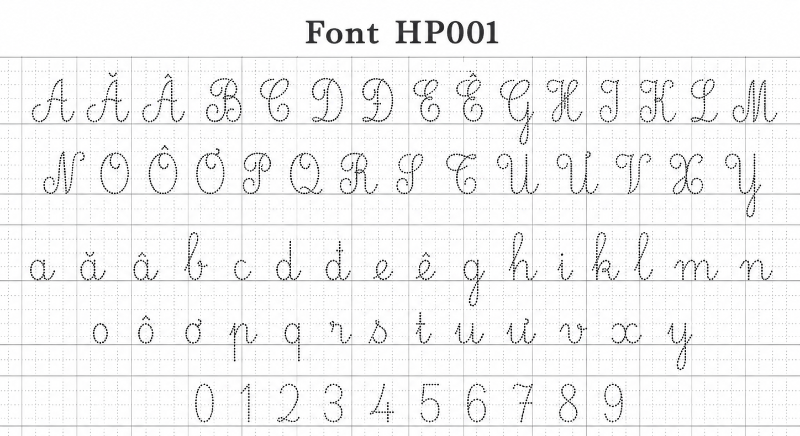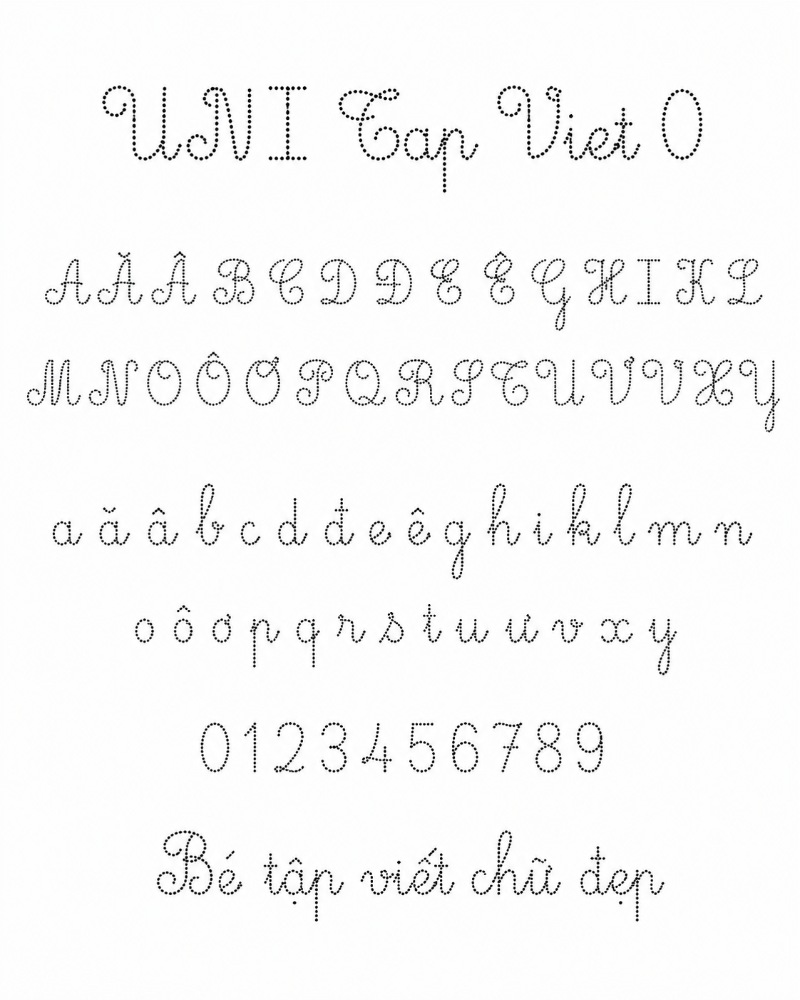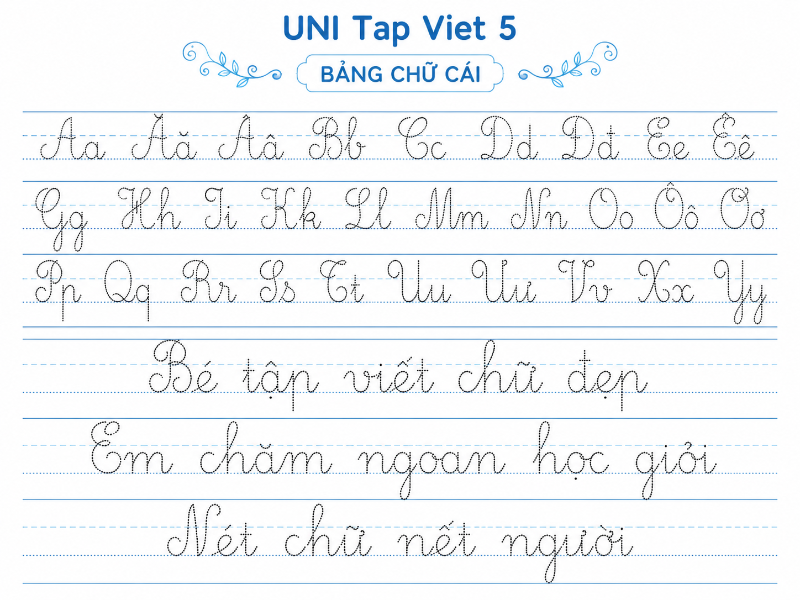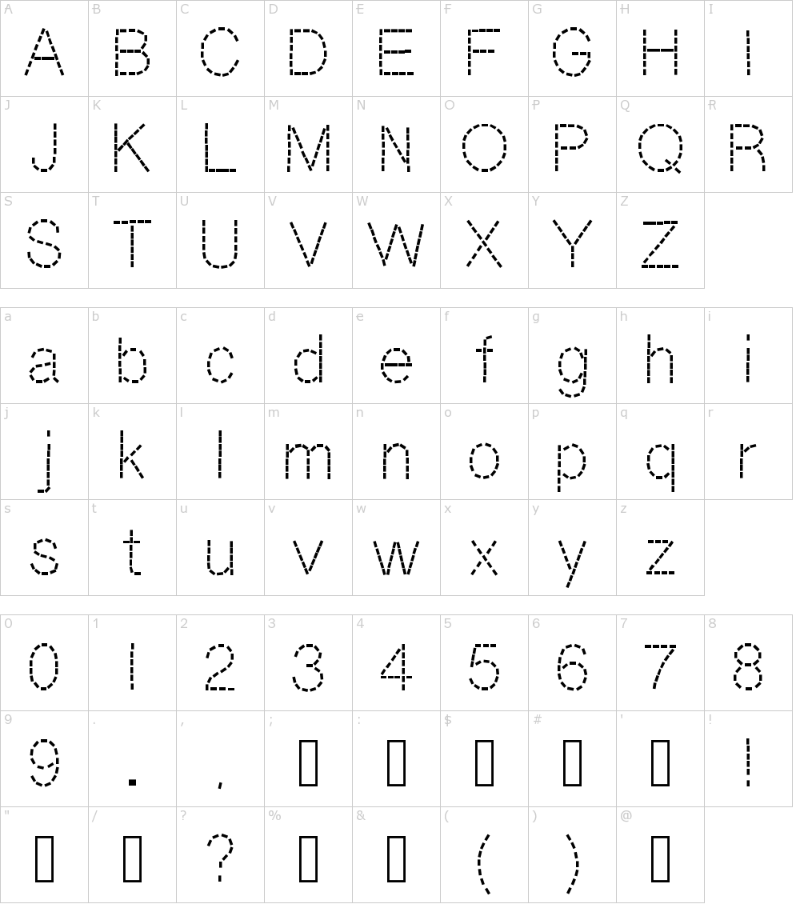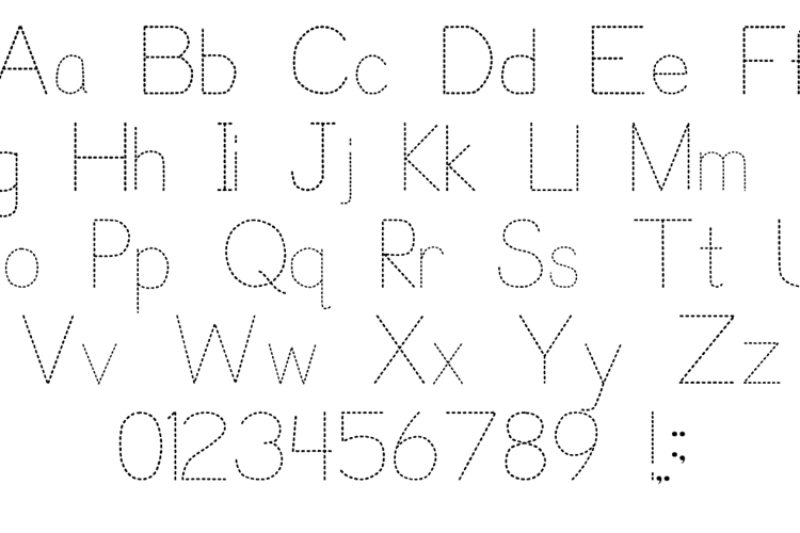
Chia sẻ 5+ Font chữ nét đứt việt hóa đẹp, dễ ứng dụng
Bạn đang mất thời gian tìm kiếm một font chữ nét đứt để thiết kế phiếu tập viết, worksheet cho bé luyện chữ tại nhà? Hoặc bạn là designer đang cần một kiểu chữ độc đáo, mang cảm giác hiện đại, công nghệ để tạo điểm nhấn cho logo, bao bì hay ấn phẩm truyền thông? Dù sử dụng với mục đích nào, bạn chắc chắn sẽ gặp một vấn đề quen thuộc: font nét đứt có rất nhiều, nhưng font hỗ trợ tiếng Việt tốt, không lỗi dấu và khi in ra vẫn rõ nét thì lại không dễ tìm.
Thực tế, không ít người tải font về, cài đặt xong và bắt đầu sử dụng, nhưng khi gõ tiếng Việt có dấu thì chữ bị lệch, lỗi ký tự hoặc tự động chuyển sang font mặc định khiến thiết kế trở nên rối mắt và thiếu chuyên nghiệp. Vì vậy, trong bài viết này, In Đại Minh sẽ tổng hợp và chia sẻ đến bạn những font chữ nét đứt đẹp, dễ dùng, phù hợp cho cả học tập, in ấn và thiết kế sáng tạo.
Font chữ nét đứt là gì?
Font chữ nét đứt, hay còn gọi là Dotted Font hoặc Dashed Font, là kiểu chữ được tạo nên từ các đường nét ngắt quãng. Thay vì liền mạch như font thông thường, từng ký tự sẽ được cấu thành bởi các chấm nhỏ hoặc những đoạn gạch rời nối tiếp nhau, tạo cảm giác rõ nét, dễ nhận diện và rất phù hợp cho nhiều mục đích sử dụng khác nhau.
Font chữ nét đứt
Hiện nay, font chữ nét đứt không chỉ xuất hiện trong các tài liệu học tập mà còn được ứng dụng rộng rãi trong thiết kế sáng tạo.
Trong lĩnh vực giáo dục, đây là một trong những công cụ quen thuộc với giáo viên tiểu học, giáo viên mầm non và phụ huynh. Font nét đứt thường được dùng để thiết kế phiếu bài tập, mẫu chữ tập tô, vở luyện viết chữ cái hoặc tài liệu rèn nét cho học sinh lớp 1. Nhờ các nét chữ được chia thành từng đoạn nhỏ, trẻ có thể dễ dàng quan sát, tô theo và làm quen dần với cách điều khiển nét bút.
Trong thiết kế đồ họa, font nét đứt lại mang đến một phong cách hoàn toàn khác. Các designer thường chọn những kiểu font nét đứt có dáng chữ mạnh, cứng cáp hoặc góc cạnh để tạo logo, poster thể thao, banner công nghệ, ấn phẩm sci-fi hoặc các thiết kế typography nổi bật. Kiểu chữ này giúp nội dung trở nên cá tính hơn, tạo điểm nhấn thị giác và tăng tính sáng tạo cho sản phẩm thiết kế.
Top các bộ font chữ nét đứt Việt hóa chuẩn hiện nay
Hiện nay có khá nhiều bộ font chữ nét đứt được chia sẻ trên mạng, nhưng không phải font nào cũng hỗ trợ tiếng Việt tốt. Dưới đây là một số bộ font đã được Việt hóa cẩn thận, hạn chế tối đa tình trạng lỗi dấu, lệch chữ hoặc tự động nhảy sang font mặc định khi sử dụng.
UNI Tap Viet 5
UNI Tap Viet 5 là bộ font rất phù hợp cho giáo dục, đặc biệt là làm vở tập viết lớp 1. Font có sẵn 5 dòng kẻ ô ly chuẩn tiểu học, nét đứt rõ ràng, giúp trẻ dễ nhìn và dễ tô theo. Bộ font này hỗ trợ cả bảng mã Unicode và VNI nên khá tiện khi dùng trên nhiều phần mềm khác nhau.
Font chữ UNI Tap Viet 5
UNI Tap Viet 0
UNI Tap Viet 0 có thiết kế đơn giản hơn vì chỉ gồm phần chữ nét đứt, không kèm đường kẻ nền phía sau. Đây là lựa chọn phù hợp để làm flashcard, bảng chữ cái, tài liệu nhận diện chữ hoặc các mẫu luyện viết cần bố cục thoáng. Font cũng hỗ trợ Unicode và VNI, giúp người dùng dễ nhập tiếng Việt có dấu.
Font chữ UNI Tap Viet 0
Trace Font
Trace Font gây thiện cảm nhờ kiểu nét đứt bo tròn, mềm mại và dễ nhìn. Font này đặc biệt phù hợp với worksheet mầm non, tài liệu tập tô chữ cái hoặc các bài luyện chữ cho trẻ nhỏ. Khả năng hiển thị tiếng Việt của Trace Font khá tốt, nhất là khi dùng với bảng mã Unicode.
Trace Font
Dashness
Dashness là kiểu font nét đứt có phong cách tối giản, thanh mảnh và tinh tế. Font không quá thiên về luyện chữ cho trẻ em mà phù hợp hơn với tài liệu văn phòng, sơ đồ, biểu đồ hoặc những thiết kế cần sự nhẹ nhàng, rõ ràng. Dashness hỗ trợ Unicode, thuận tiện khi soạn thảo tiếng Việt.
Font chữ Dashness
Font HP001
Nếu bạn đang cần thiết kế tài liệu tập viết có giao diện giống vở ô ly học sinh bán tại nhà sách, font HP001 là một lựa chọn rất đáng dùng. Bộ font này phù hợp để tạo phiếu luyện chữ, bài tập tô chữ hoặc tài liệu dạy viết cho học sinh tiểu học.
Điểm mạnh của HP001 nằm ở khả năng mô phỏng nét chữ thanh – đậm khá chuẩn, giúp chữ viết hiển thị tự nhiên và gần với mẫu luyện viết truyền thống. Ngoài ra, font còn hỗ trợ cả dạng 4 ô ly và 5 ô ly, kèm hệ thống ký tự đặc biệt để người dùng có thể tạo khung lưới ô ly ngay khi soạn thảo, tiết kiệm thời gian căn chỉnh thủ công.
Font HP001
Việc sử dụng font chữ nét đứt không chỉ giúp các bậc phụ huynh, giáo viên tiết kiệm chi phí mua sách vở mà còn giúp các Designer thỏa sức sáng tạo. Hy vọng với những font chữ nét đứt được chia sẻ trên đây, bạn đã có thể tự tay tạo ra những ấn phẩm xuất sắc.